巧用笔刷,就可以在AI里定制独家字体!
在之前的一篇文章中,我们曾给大家介绍一种简便的字体设计方法「笔画置换」,得到了大家不错的反响。今天,我们将再一次从修改笔画的外观出发,给大家介绍多种超简单的字体设计方法,只需要用到AI软件自带的功能或添加笔刷就能轻松完成。好啦,我们话不多说,上车吧!
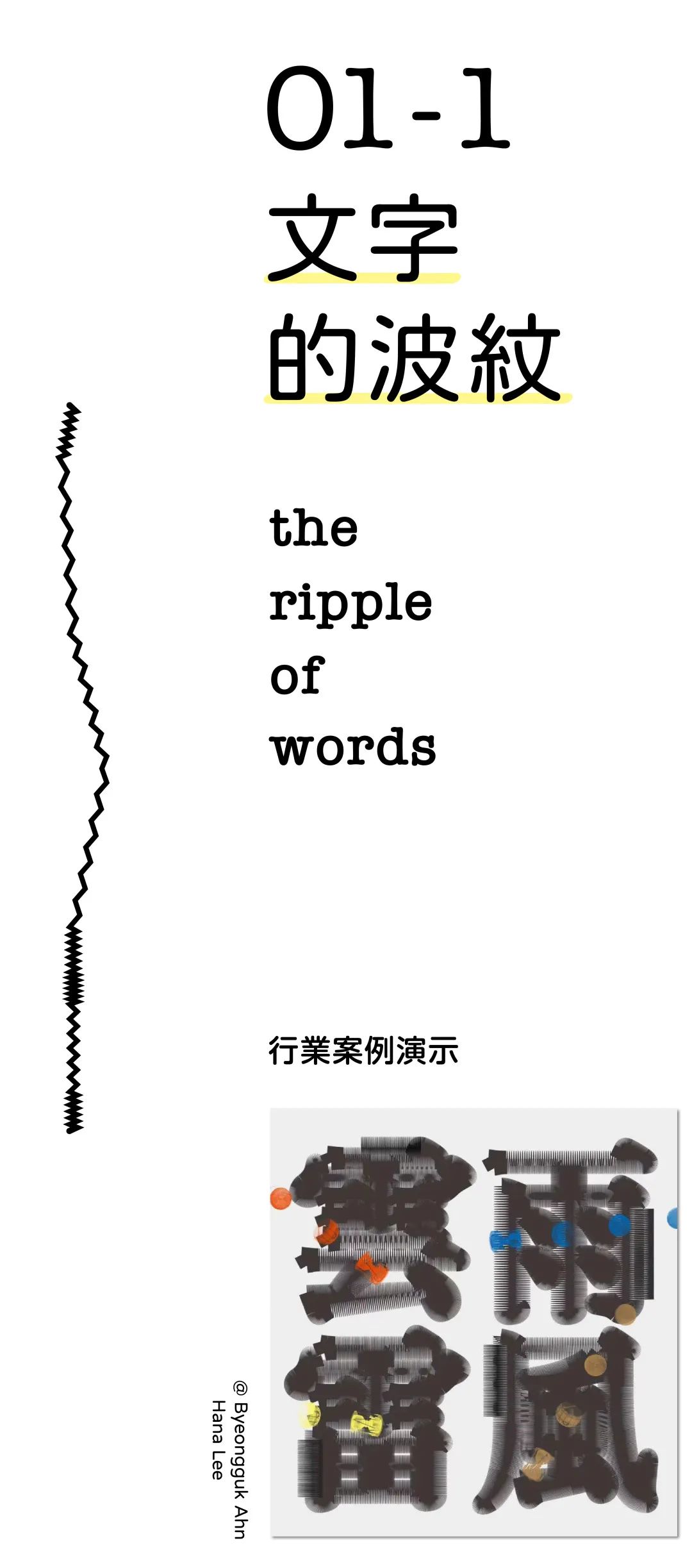
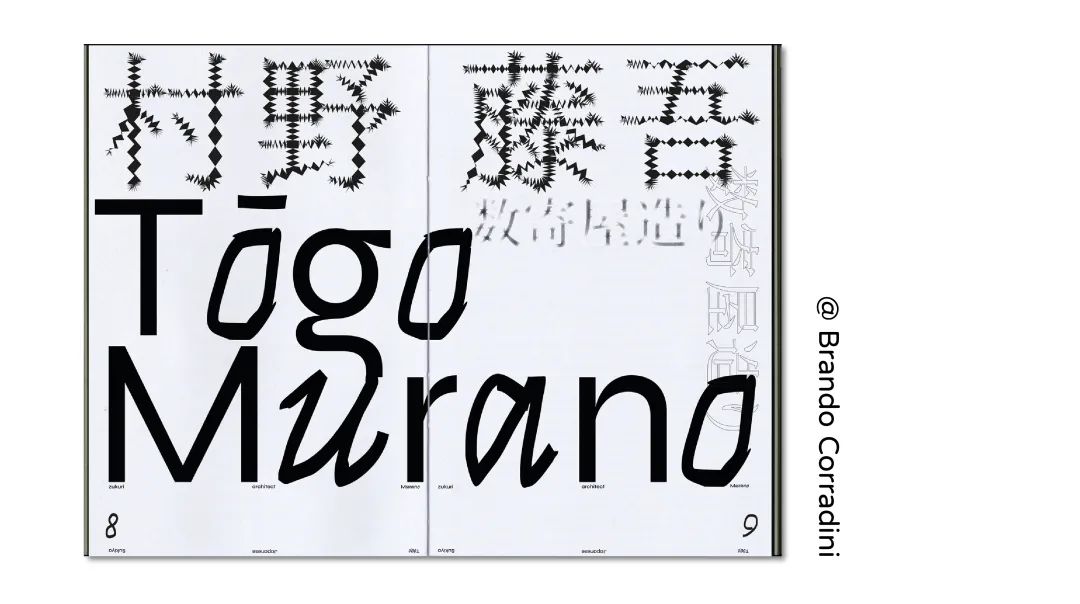
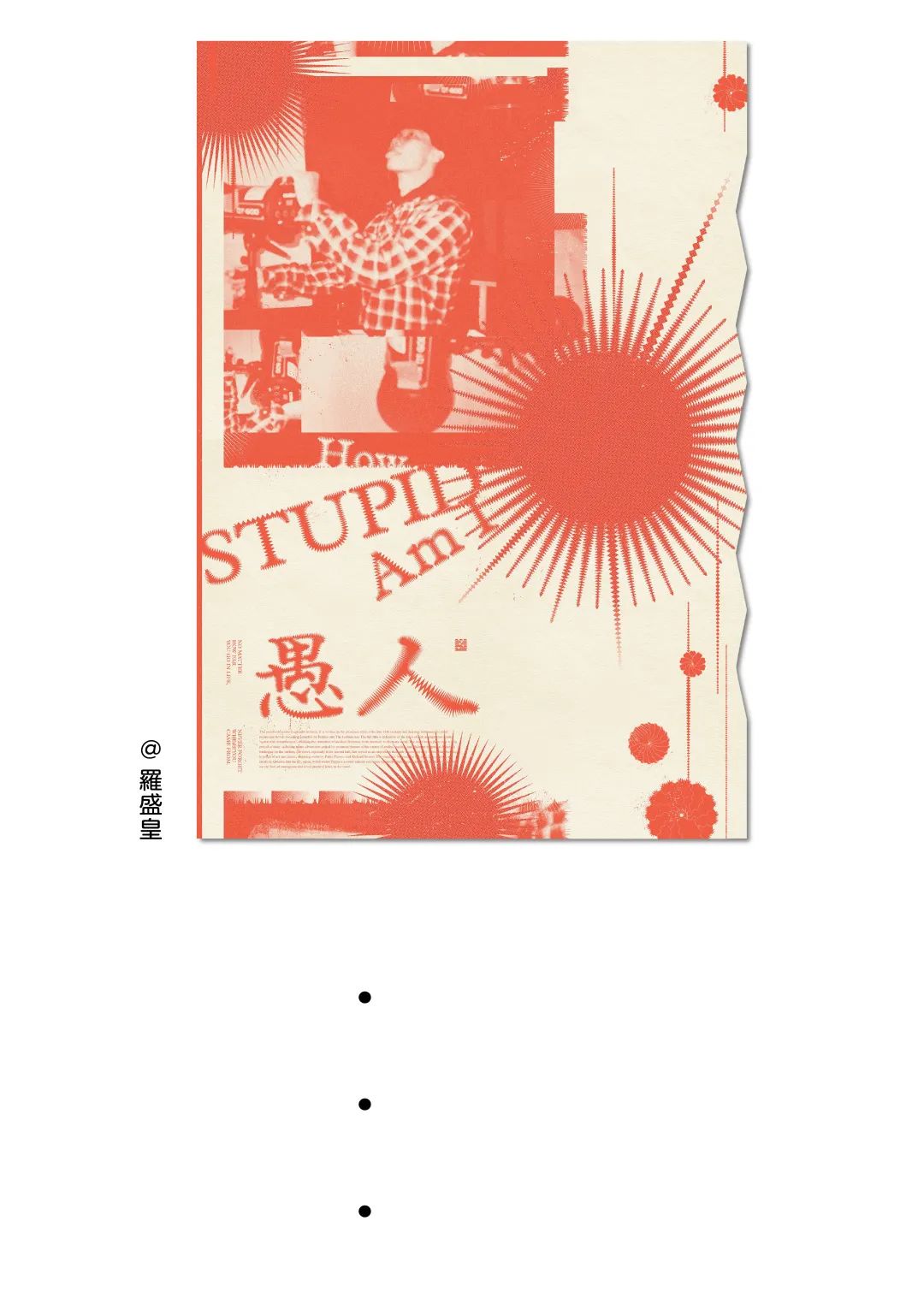
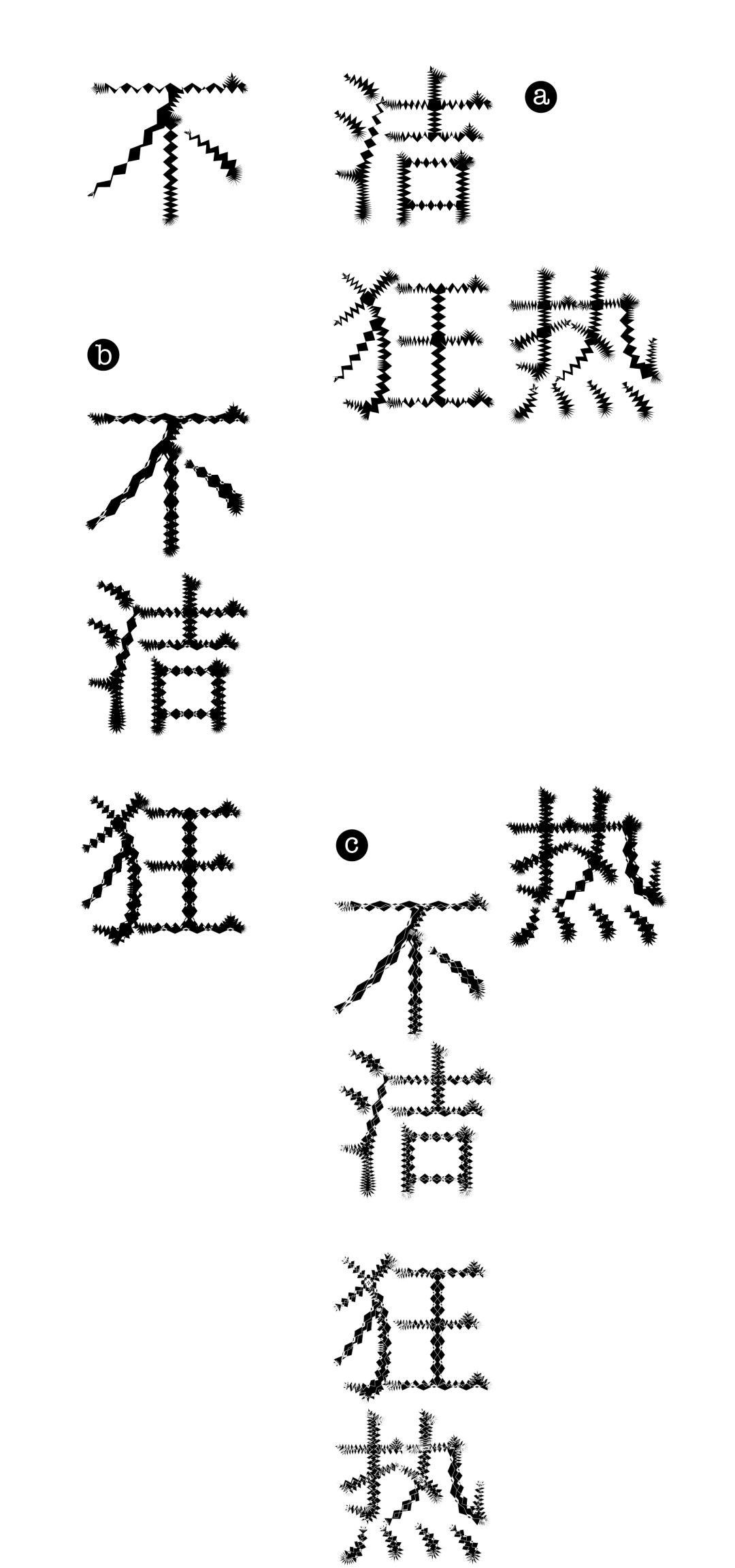
以上就是今天从修改笔画外观出发的,超简单字体设计方法的全部内容了。相信大家也都能感觉到,只要合理利用设计素材和软件功能,往往就能达到事半功倍的效果。大家也可以自行多做试验,没准能发现属于自己的独家设计套路。好了,我们下次再见,拜拜:-)